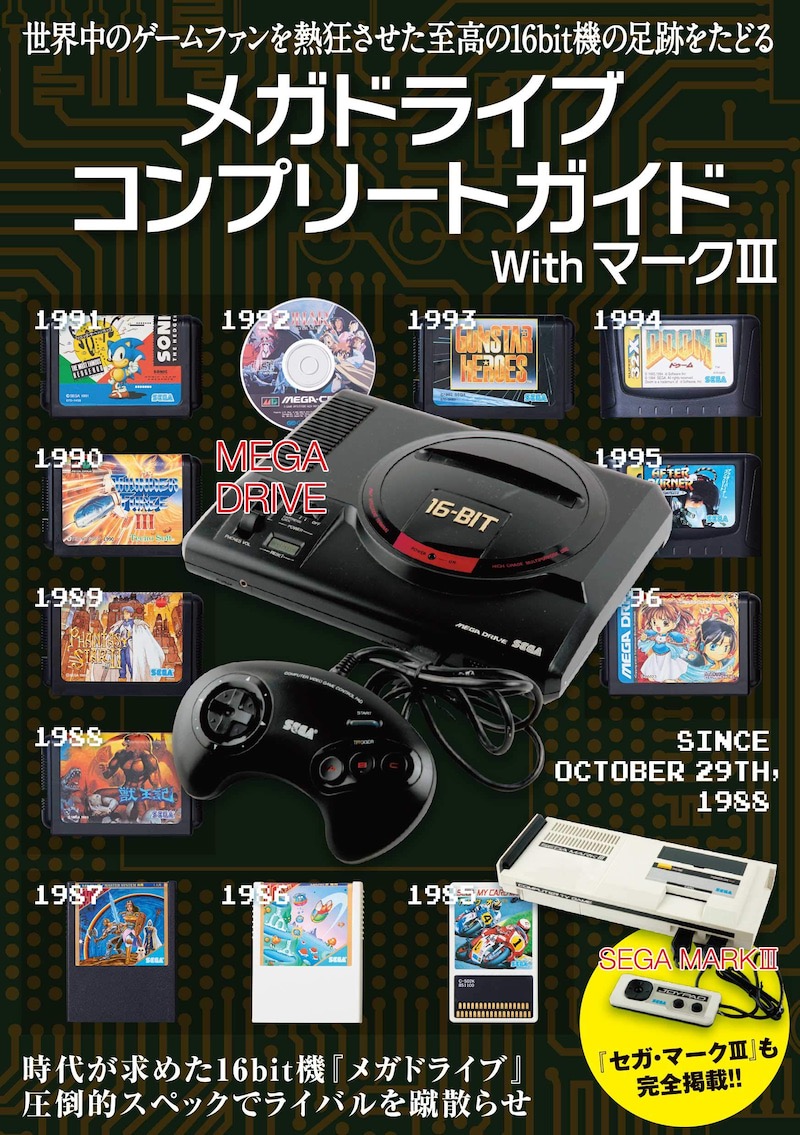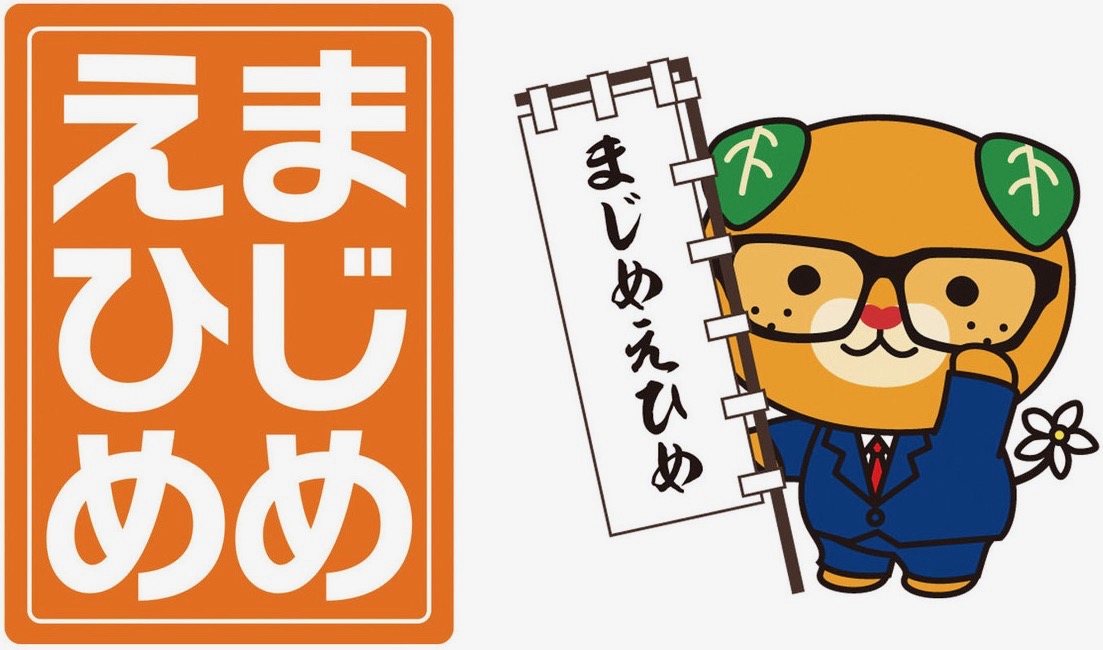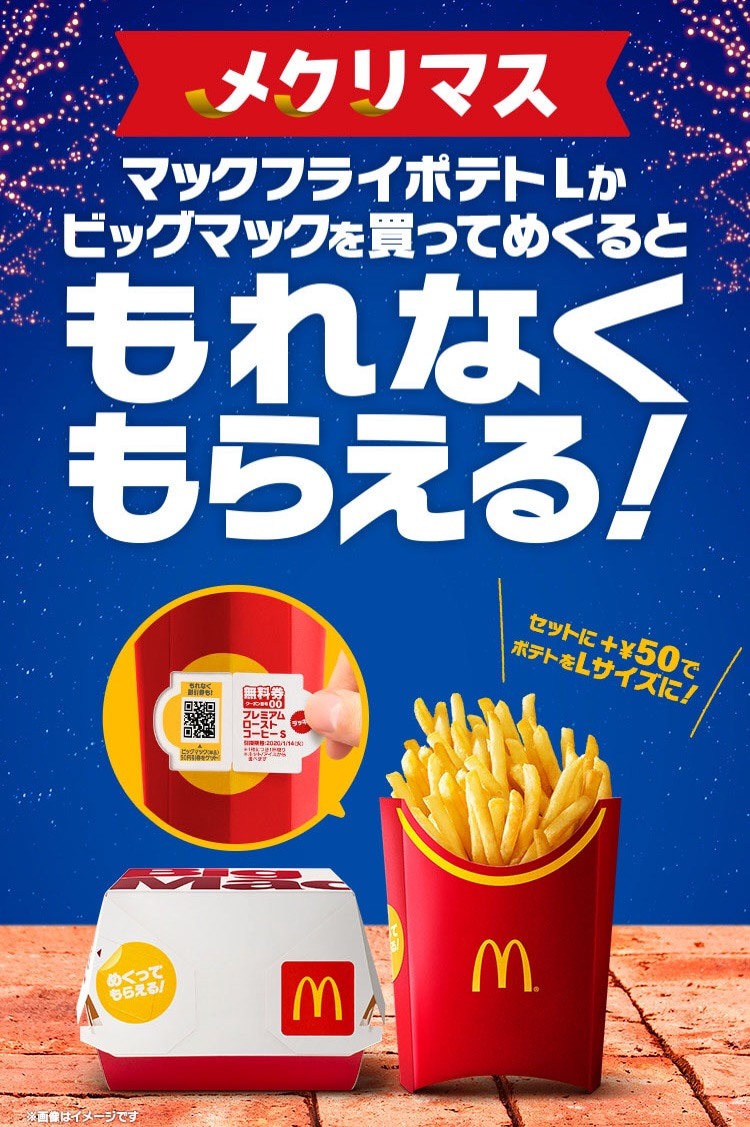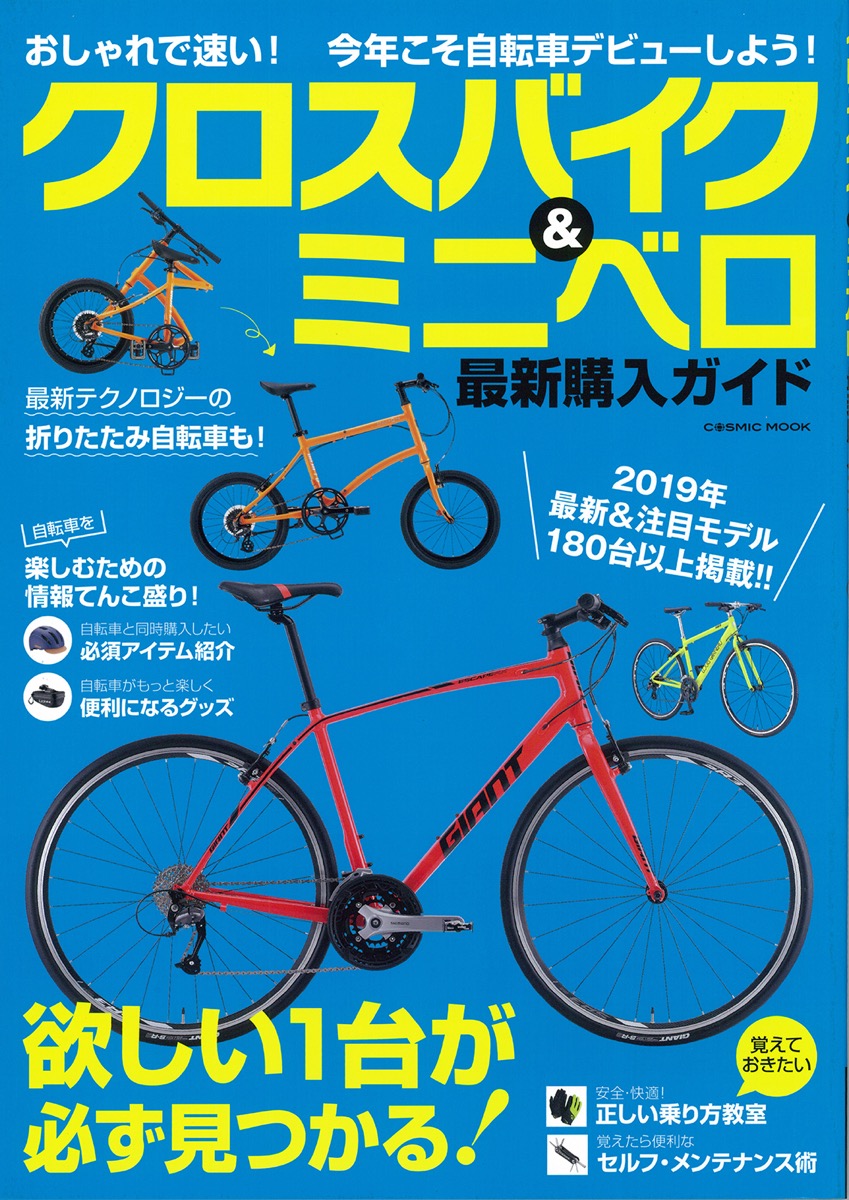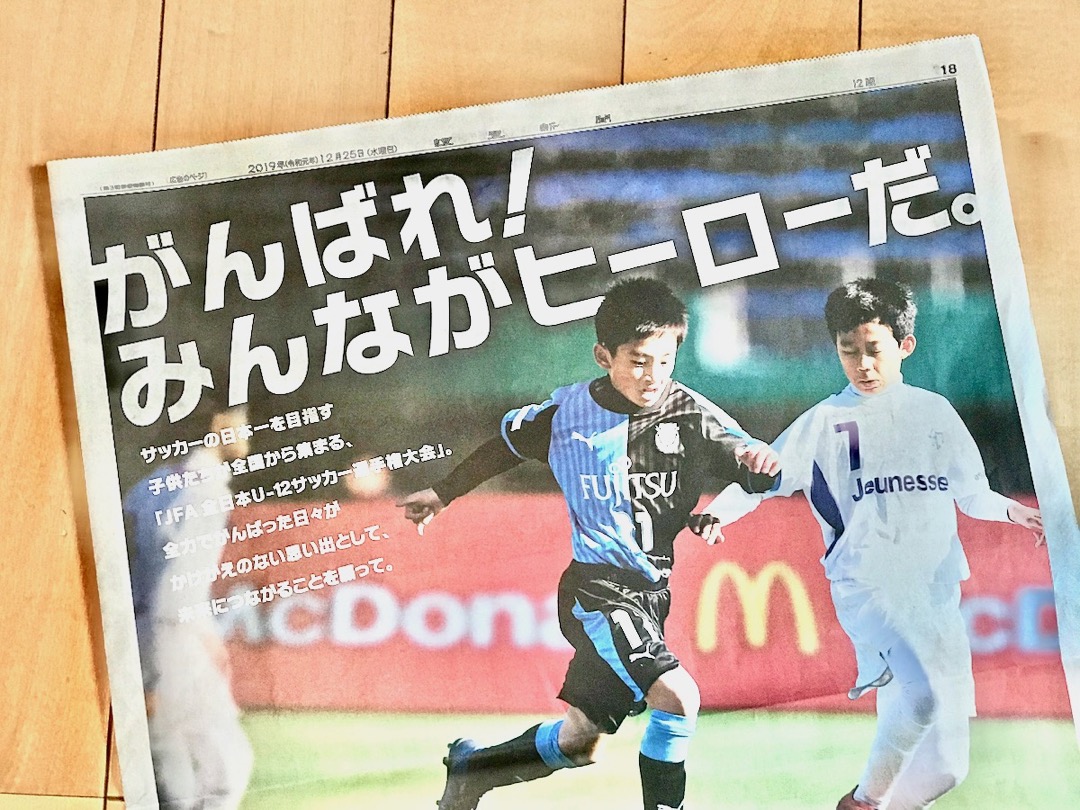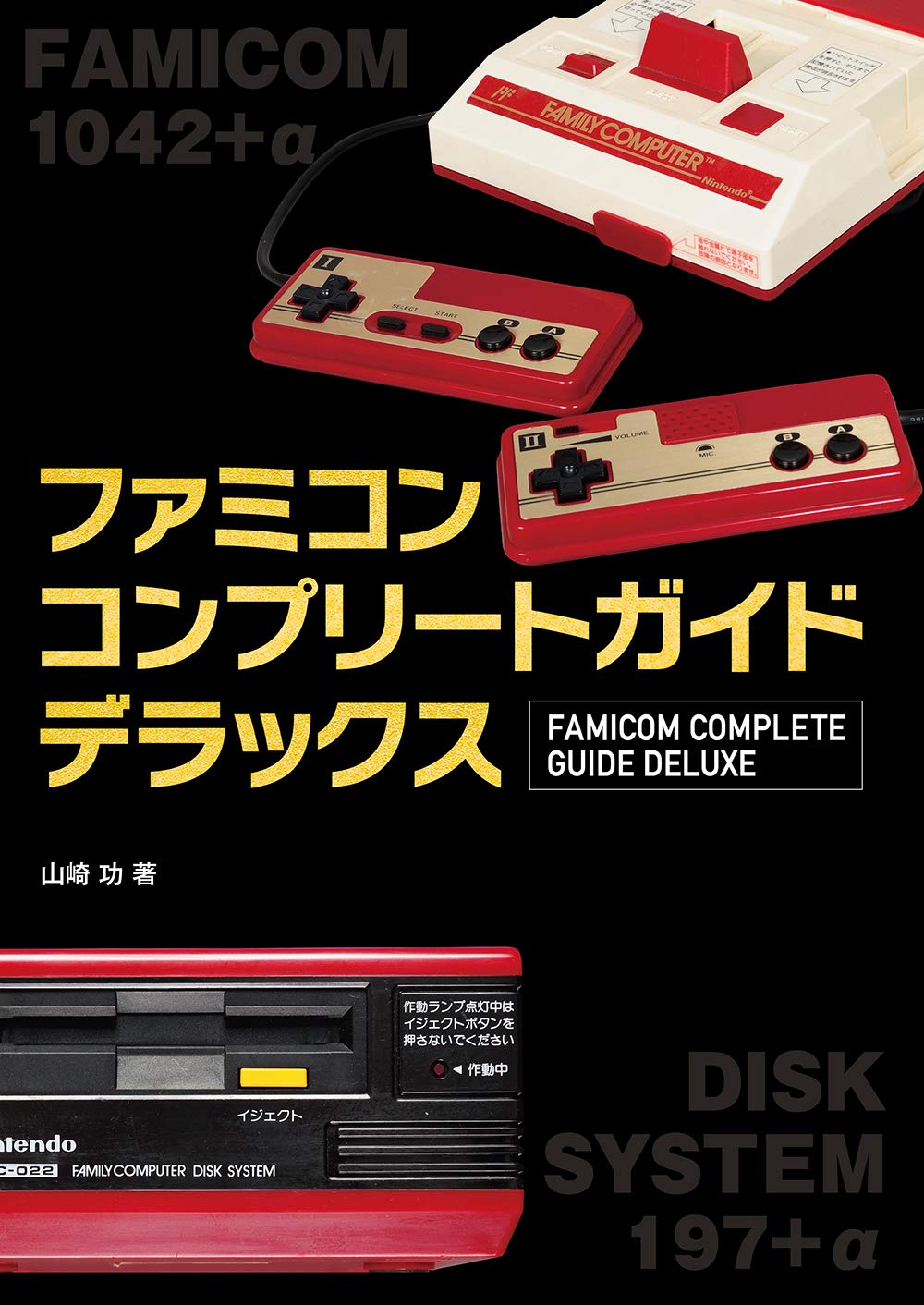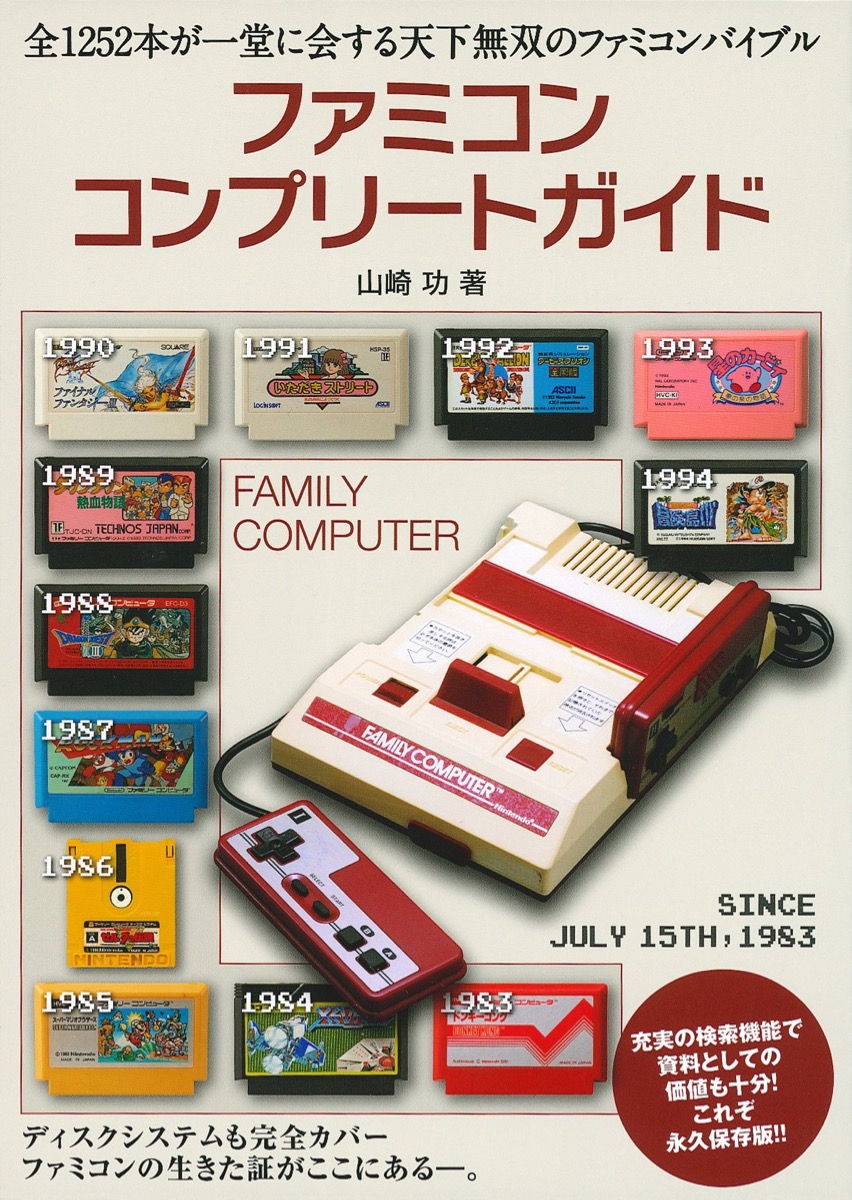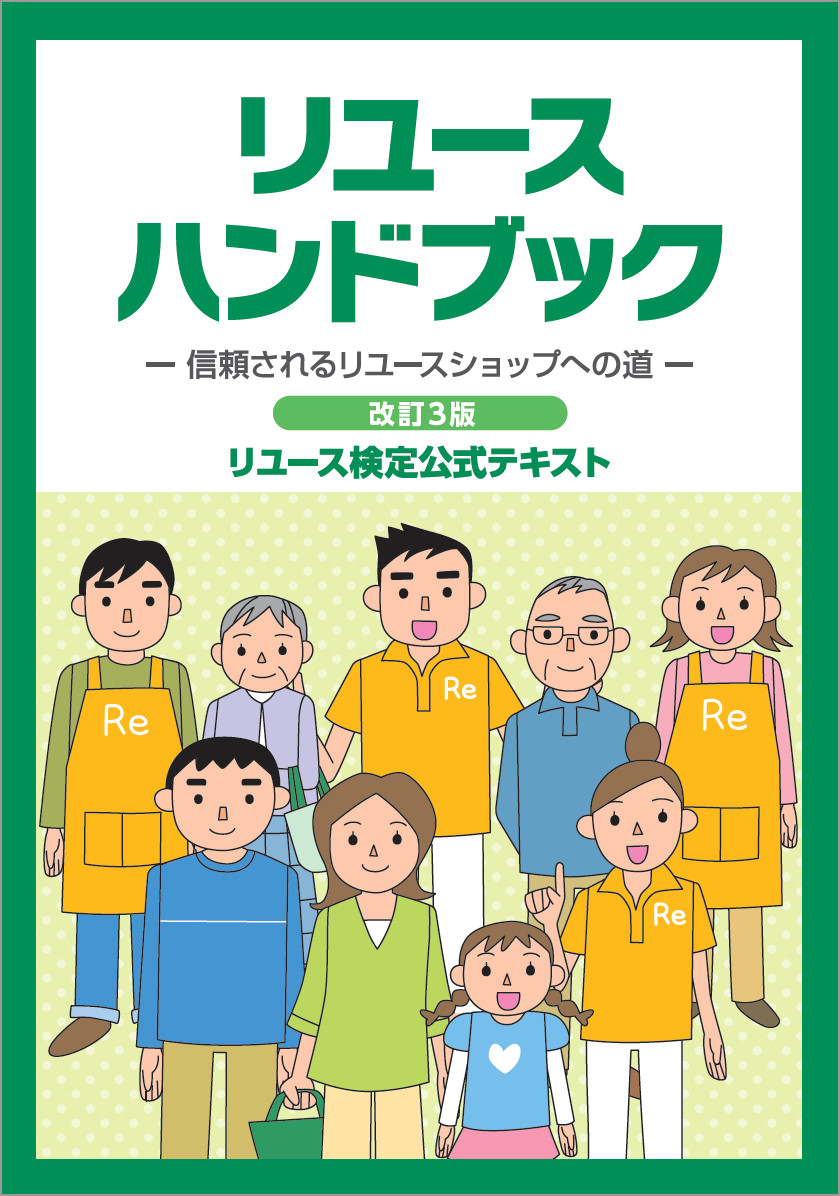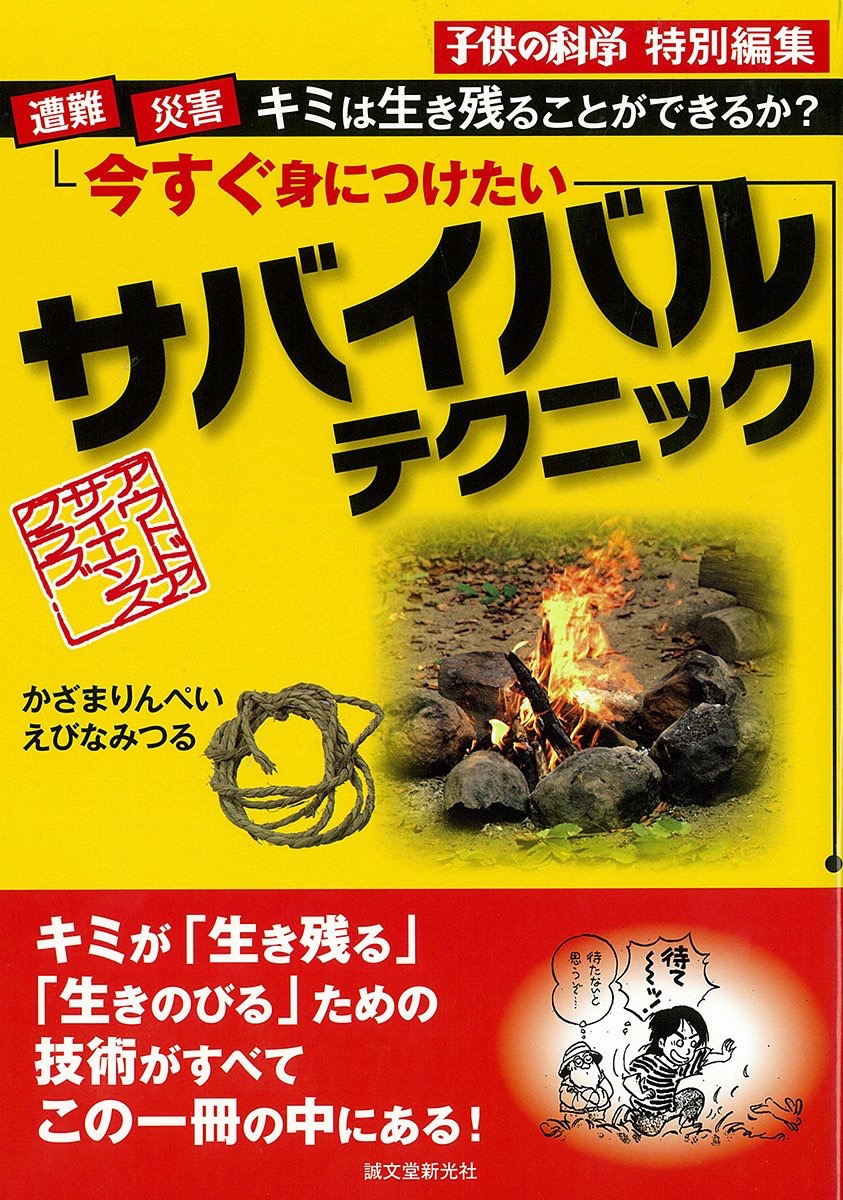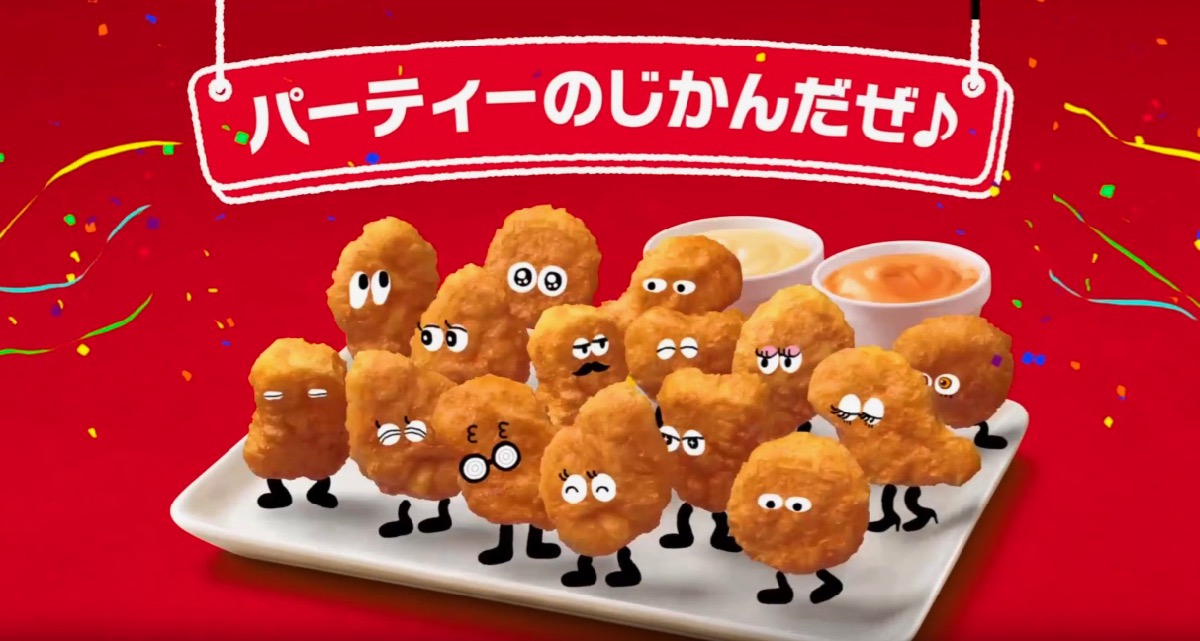
野球中継画面 さとうゆたか
NHK-BSのMLBの中継。
ポスター さとうゆたか
東武線のホームなどに貼られているマナーポスター。
テレビ番組 さとうゆたか
テレビ朝日の「裸の少年」。
CM さとうゆたか
JR東海のCM。
屋外の案内板 さとうゆたか
浜名湖の遊覧船乗り場の近くで。
映画ポスター さとうゆたか
これも…。
スパイシーチキン さとうゆたか
マクドナルドの広告画像。
これも…
こちらは動画。
ニタラゴを丸ゴに さとうゆたか
かな書体「ニタラゴ」を丸ゴシック化した「ニタラゴ丸」を作りました。
丸ゴシック「レラ」と組み合わせて総合フォントにします。
これが昨日頒布開始した、レラと組み合わせた「ニタラゴレラ」です。
WEBフォントでも さとうゆたか
アニメ作画の参考書 takumi
ニタラゴが使われている本の表紙を見つけました。
太さ違いも含め、たくさん使われていますね。
飲料のロゴ さとうゆたか
下町の酒場で見かけるバイスサワー。